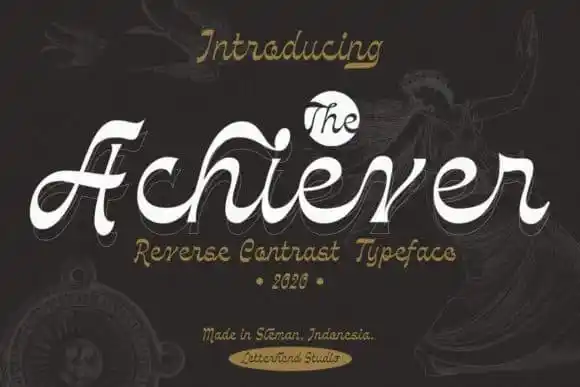
The Achiever Script Font – Download Grátis
A fonte “The Achiever Script Font” é uma escolha perfeita para qualquer projeto que deseje dar um toque único e elegante à sua criação. Ela traz consigo a encantadora combinação de um estilo clássico moderno, adaptado com elementos contemporâneos, criada por um talentoso designer do 99designs. Através dessa fonte script, você pode explorar uma estética que evoca tanto elegância quanto o charme vintage da escrita manual. A “The Achiever Script Font” não apenas oferece beleza inegável e um toque vintage, mas também consegue se destacar em uma variedade de criações. Suave e única na sua essência, ela transformará seus projetos em algo absolutamente notável. Este é o tipo de fonte que você deseja encontrar no seu coquetel de ferramentas digitais. Aproveite a oportunidade para dar um novo impulso ao design do seu próximo projeto com “The Achiever Script Font”.